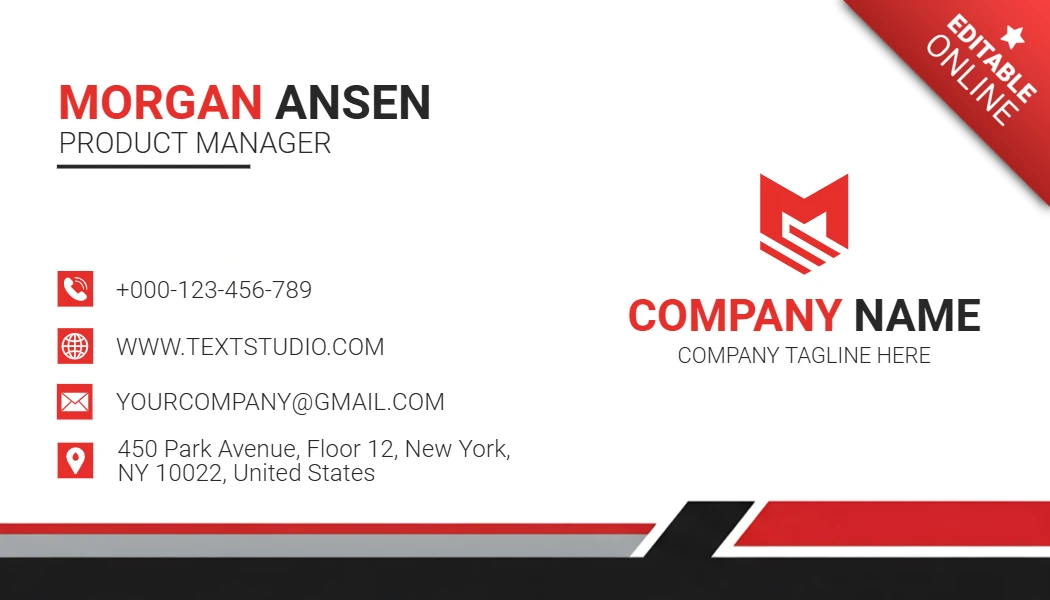
Design de carte de visite moderne minimaliste avec des accents rouges audacieux et une typographie épurée.
Éditer dans Design Studio Télécharger en JPGÉlevez votre image de marque avec notre modèle de carte de visite moderne et minimaliste, présentant des accents rouges audacieux et une typographie épurée—parfait pour le réseautage et l'établissement d'une identité d'entreprise professionnelle.